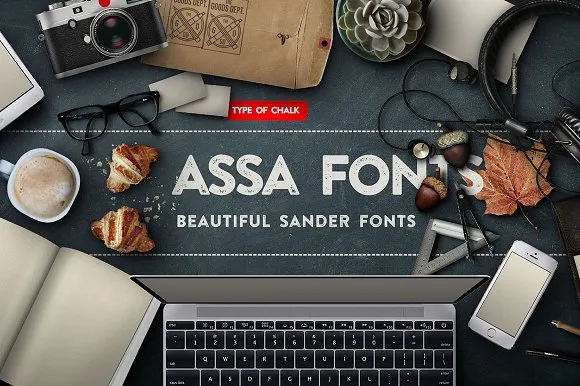
Assa Typeface – Download Grátis
Introduzimos a você uma nova fonte exibicional chamada Assa Typeface. Criado pelo Designer 178-MC, essa fonte é exclusivamente do estilo Chalk. O designer Monsterfonts apresentou ao público um design único e divertido, especialmente indicado para as necessidades da área de supply e logo design. Assa Typeface é uma excelente escolha para quem deseja dar um toque vintage em seus produtos ou ambientes comerciais, como cafeterias, vapores shops ou até mesmo lojas com temáticas antigos. Eu acho que Assa Typeface seria perfeitamente adaptada para estilos vintage e boêmios, promovendo uma atmosfera única e encantadora. Aproveite o poder desta fonte na próxima criação gráfica de seu negócio!